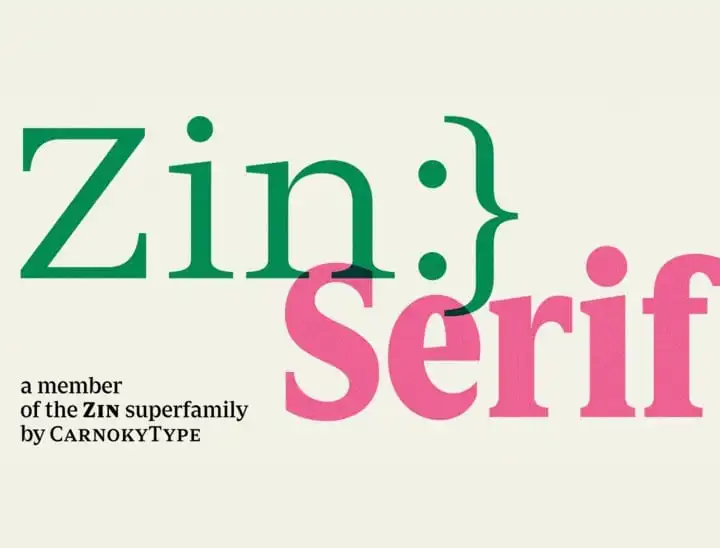
Zin Serif Font é uma família de serif moderna inspirada no renascimento dos estilos antigos. Cada caracter foi cuidadosamente moldado por CarnokyType para manter elegância e clareza legível, ideal para diversos ambientes gráficos. Com um espaçamento x-height acentuadamente alto e equilíbrio entre os elementos neutros das letras (com uma orientação vertical) e os formados abertos e dinâmicos, Zin proporciona uma experiência de leitura envolvente. Outra característica notável é o visualmente reduzido espaço entre as linhas do corpo de letra e as linhas que a acompanham. Estas propriedades tornam a Zin Serif Font um recurso valioso para designers, especialistas em design de gráficos e estudiosos interessados em fontes com estilo tradicional. Ela é perfeita para criar textos profissionais, jornalismo digital e identidades visuais, mantendo uma estrutura sólida e dinâmica ao mesmo tempo.